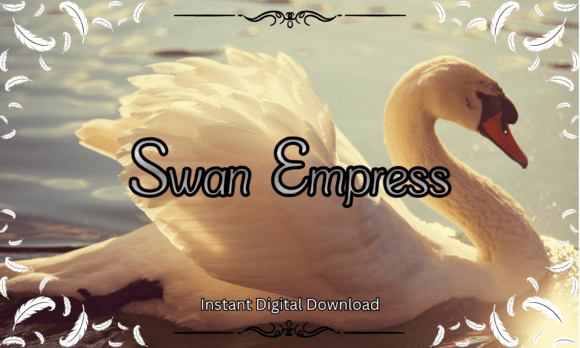
Swan Empress
Trouver les bons éléments de conception peut être un défi, mais Swan Empress propose une collection exceptionnelle qui rehausse instantanément votre travail.
Que vous créiez des produits POD (impression à la demande), des invitations de mariage ou des visuels pour les réseaux sociaux, Swan Empress est un choix idéal.